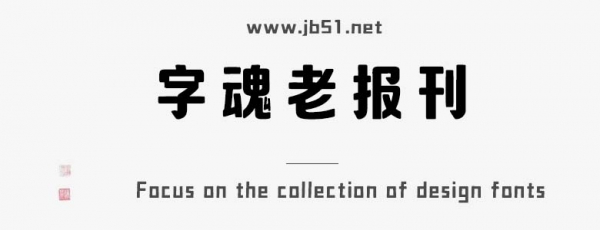
字魂老報(bào)刊字體由字魂字庫推出的創(chuàng)意標(biāo)題字字體,該字體包含9503個(gè)中文、字母、 符號(hào)和數(shù)字,具有復(fù)古傳統(tǒng)的風(fēng)格,適合應(yīng)用于藝術(shù)設(shè)計(jì)、平面宣傳設(shè)計(jì)、網(wǎng)頁設(shè)計(jì),書法字帖等領(lǐng)域。
字魂老報(bào)刊字體是一款商用的黑體,創(chuàng)意標(biāo)題字字體,該字體包含9503個(gè)中文、字母、 符號(hào)和數(shù)字,具有復(fù)古傳統(tǒng)的風(fēng)格,可以滿足您設(shè)計(jì)上的各種需求,該字體主要用于地產(chǎn)置業(yè)等場(chǎng)景, 您不但可以在字魂網(wǎng)下載字魂老報(bào)刊字體,同時(shí)還有眾多毛筆書法字體、創(chuàng)意字體等可供選擇!